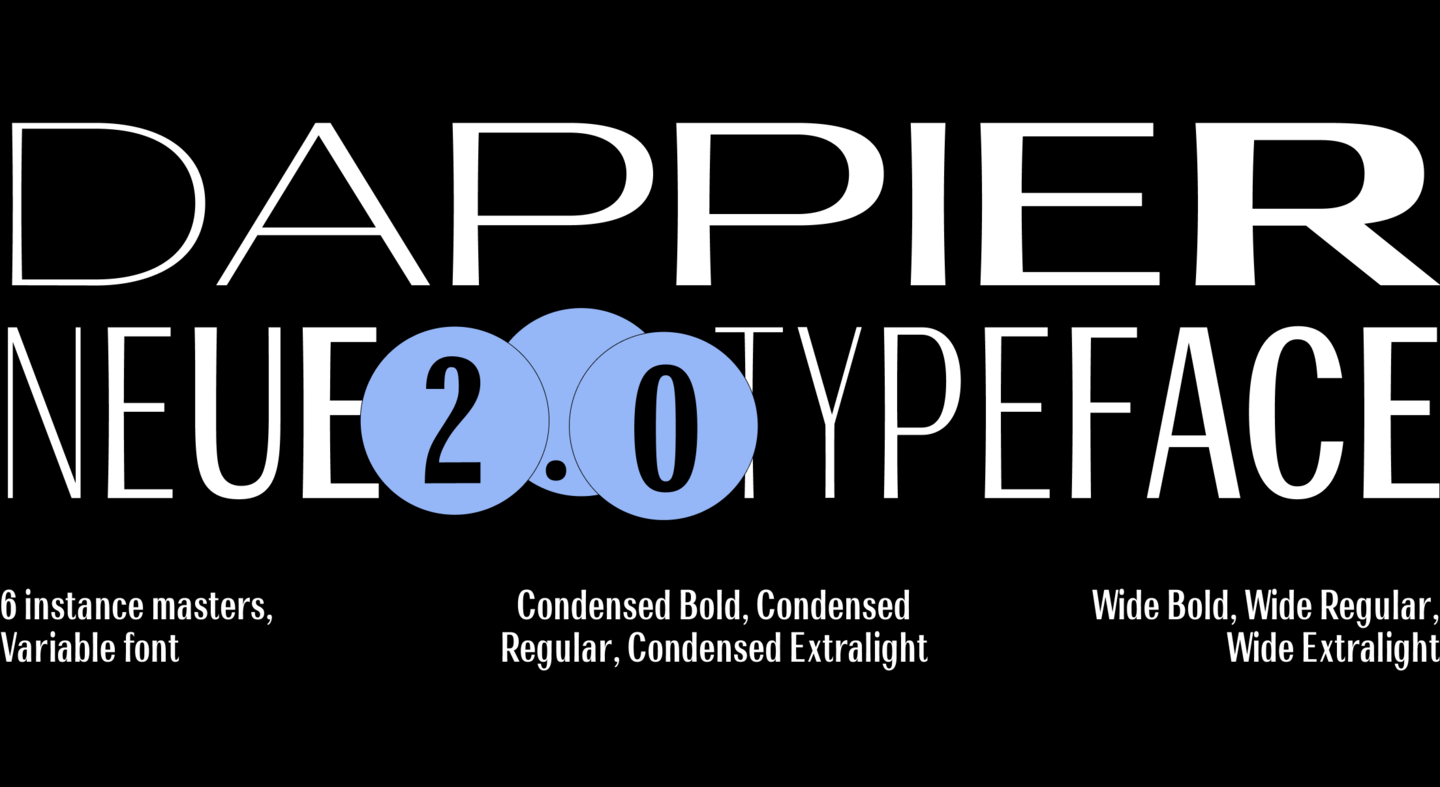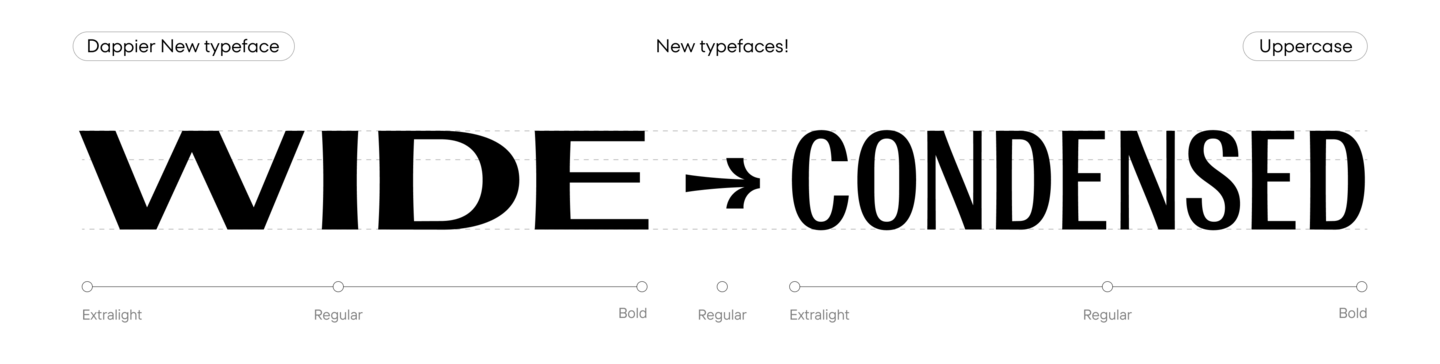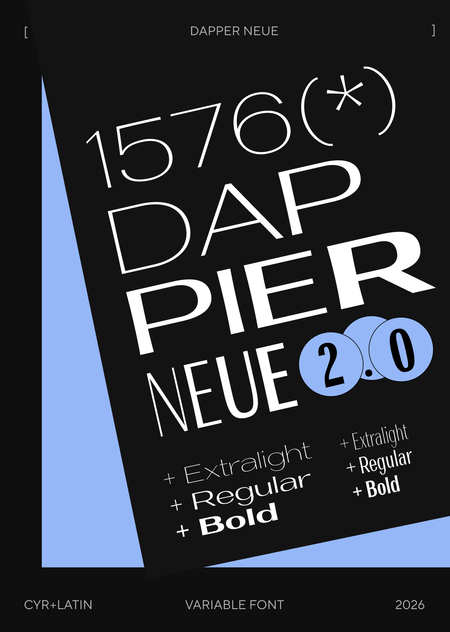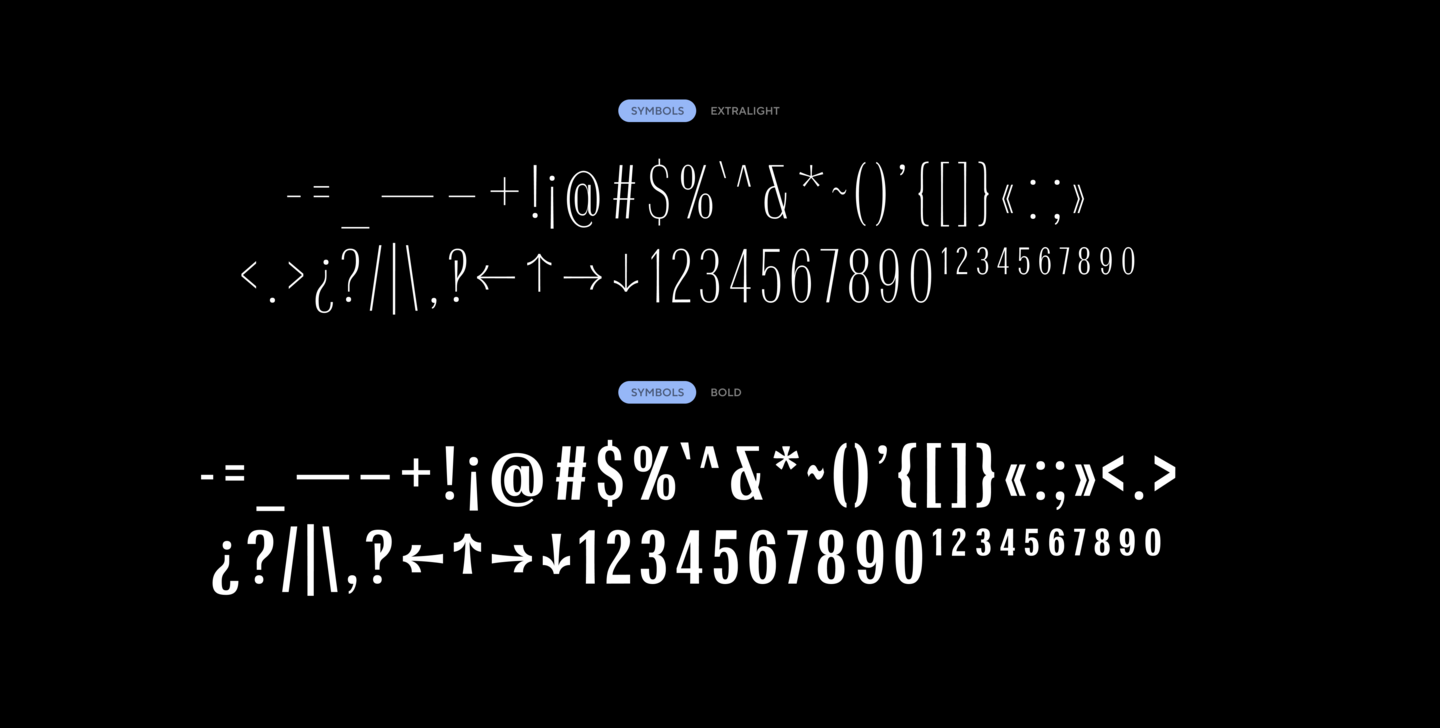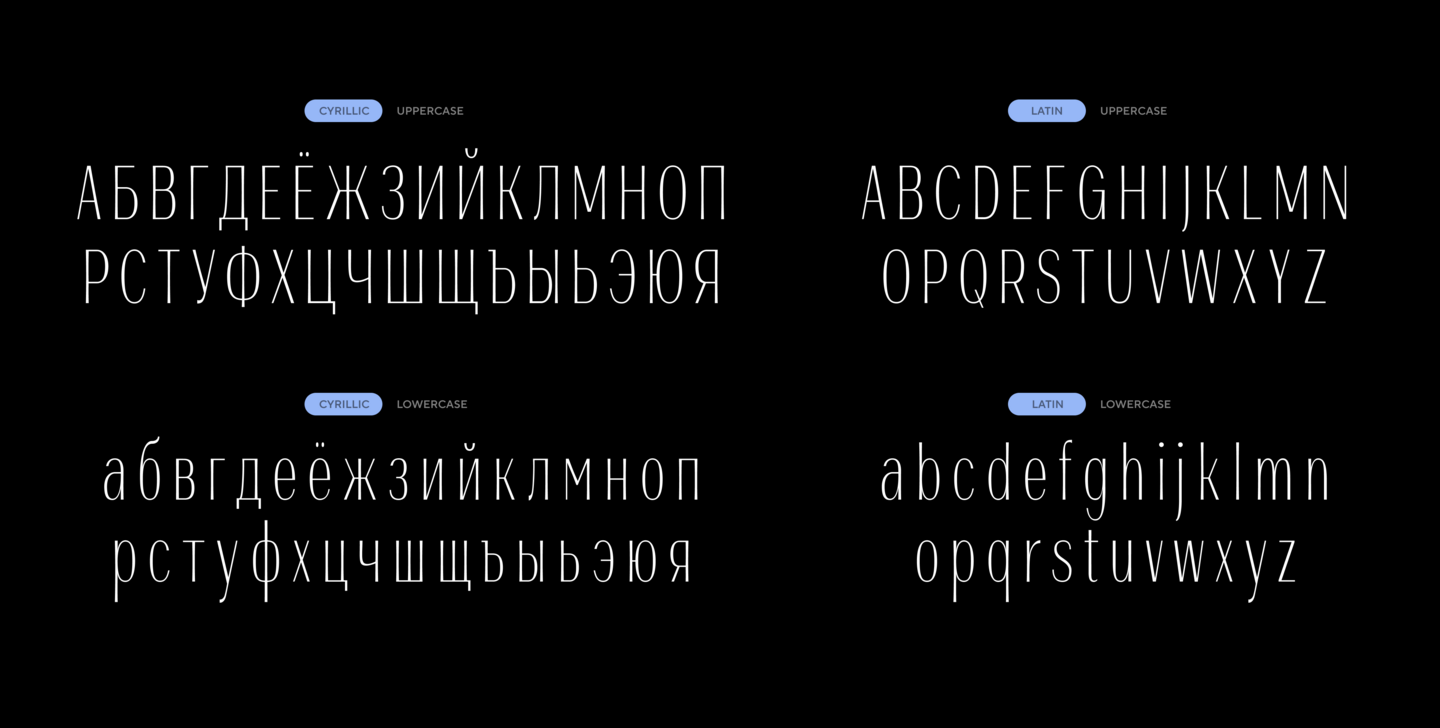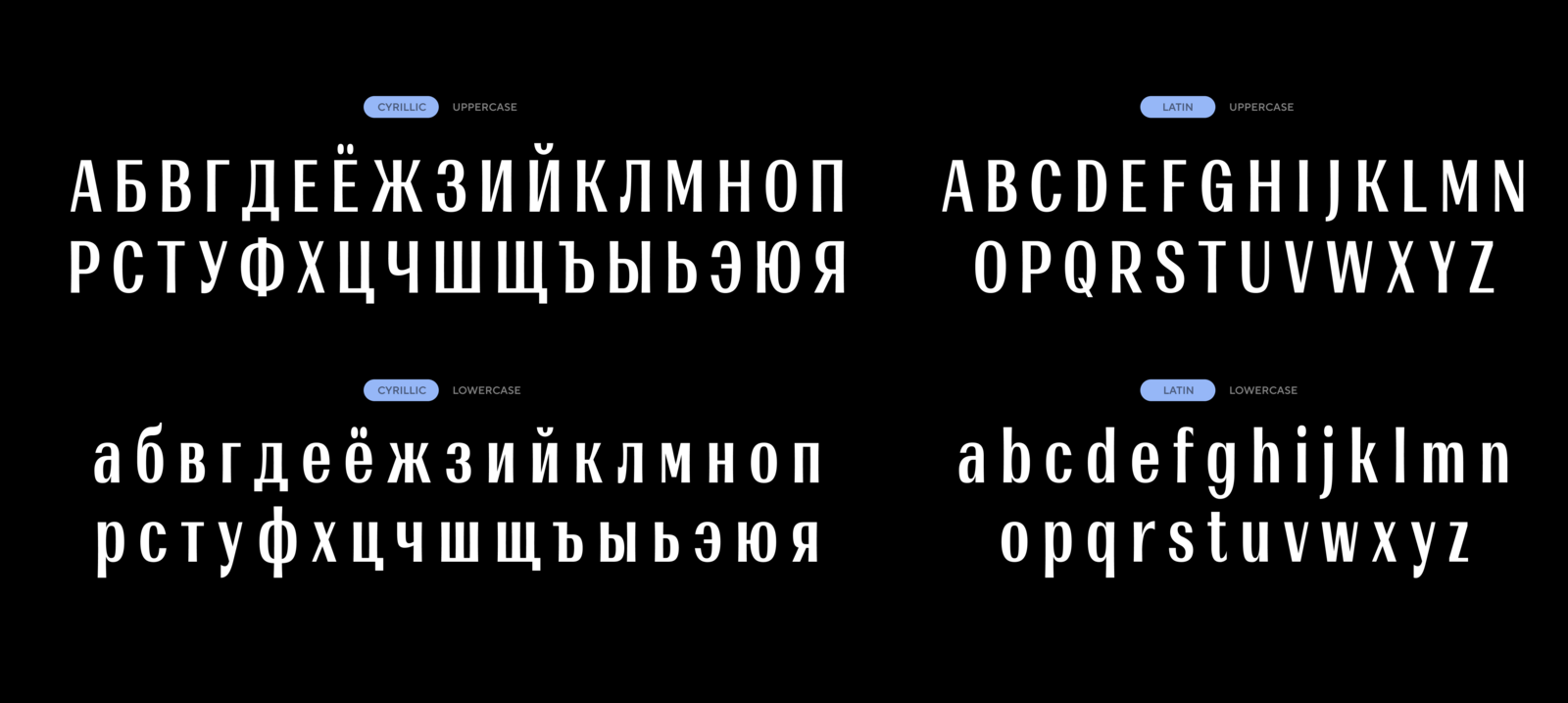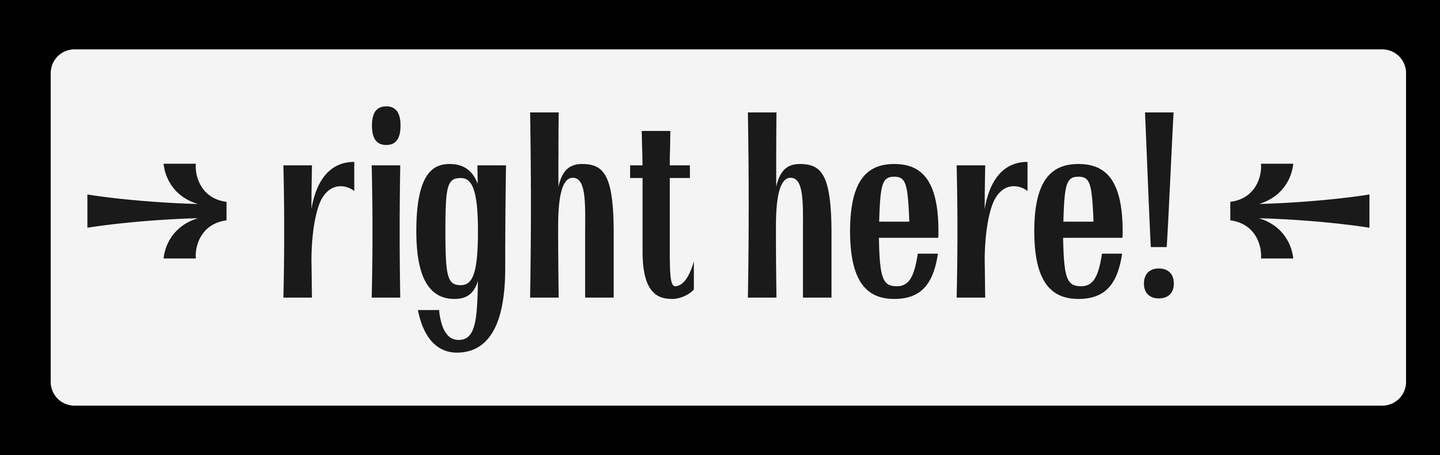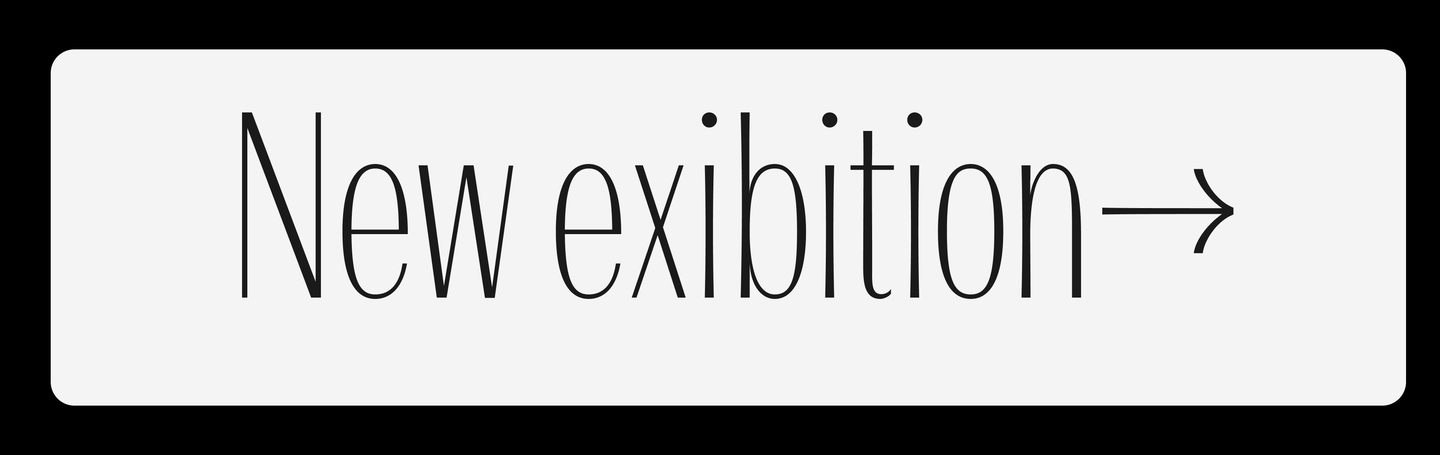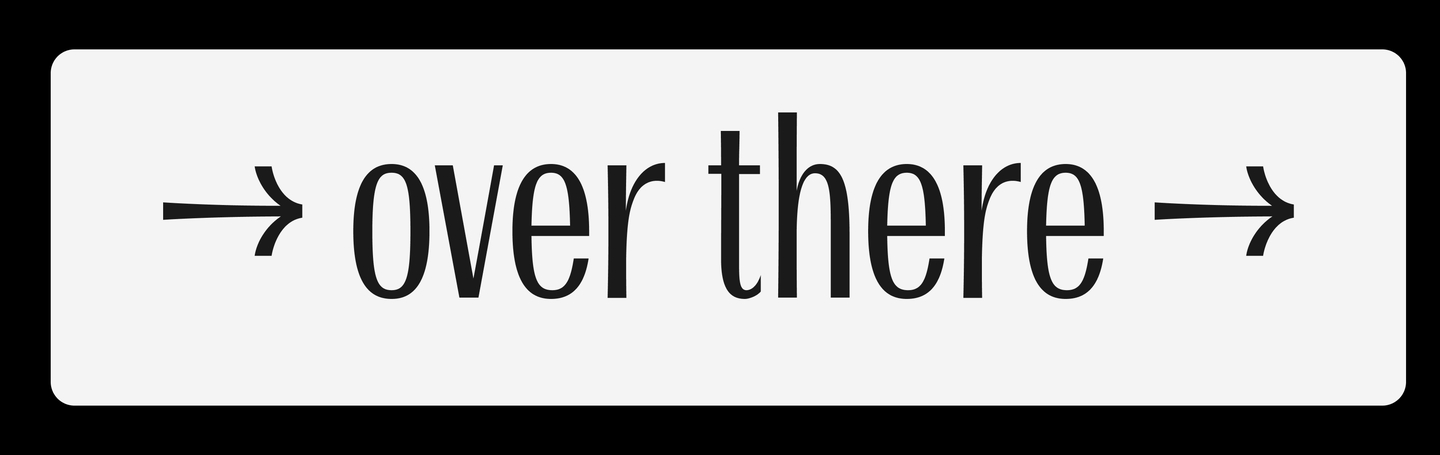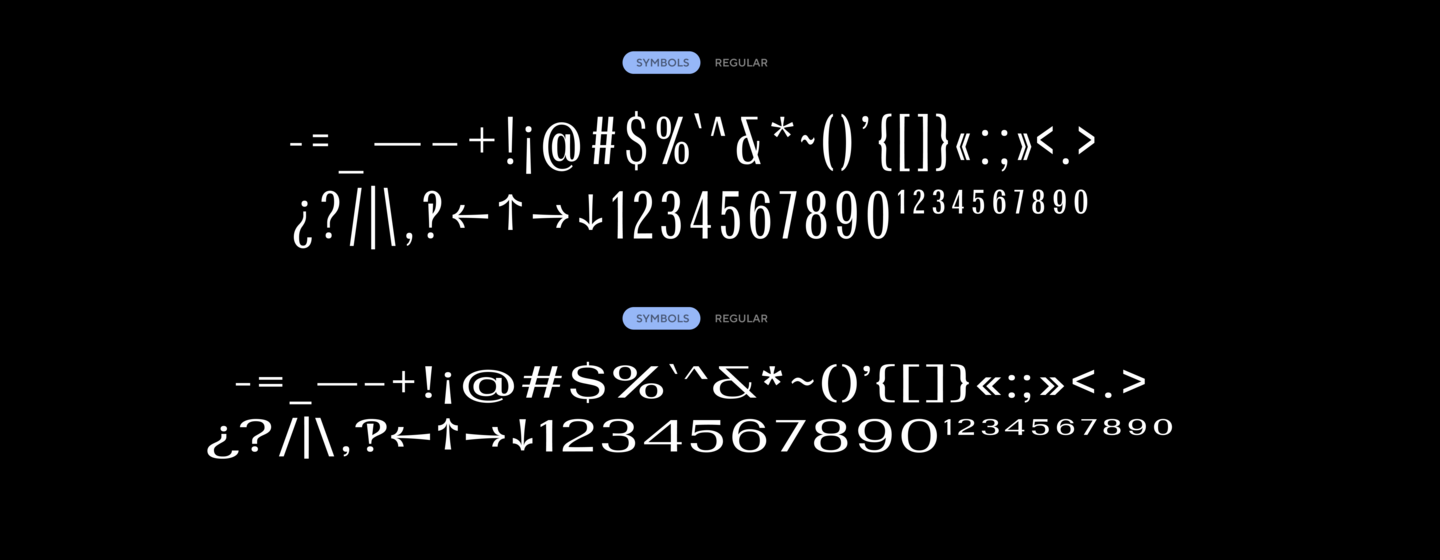
Dappier Neue — обновленная версия вариативной широкой ленточной антиквы с аккуратным контрастом.
Добавлена новая ось вариативности Wide — Condensed и начертание Regular.